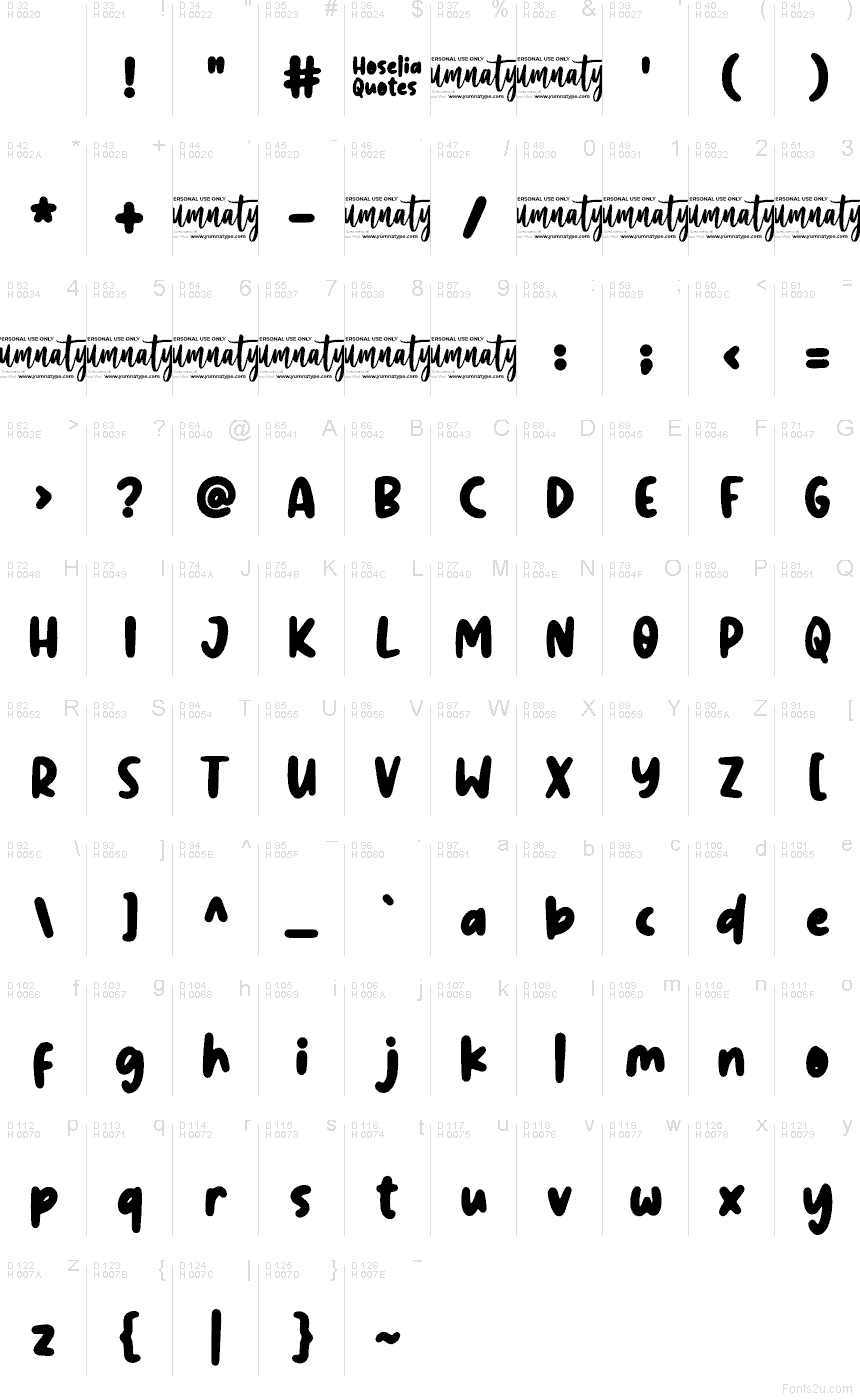
Hoselia Quotes od Yumnatype je bezplatné kreslené písmo s měkkými, nadýchanými písmeny, která vypadají jako tvarovaná rukou a mají lehce gumový nádech. Zaoblené tvary, zúžené spoje a hravá dynamika dodávají fontu uvolněný komiksový tón, zatímco nepravidelný rytmus zabraňuje tomu, aby působil příliš hladce nebo mechanicky.
Hodí se na nadpisy plakátů, obálky dětských knih, obaly na svačiny, pozvánky na večírky a příspěvky na sociální sítě, kde potřebujete bezplatné písmo, které je přátelské, ale ne přehnaně cukrkandlové. Protože jsou písmena robustní a trochu netradiční, skvěle fungují i pro krátké titulky, skici log a velké citace, které mají působit neformálně.